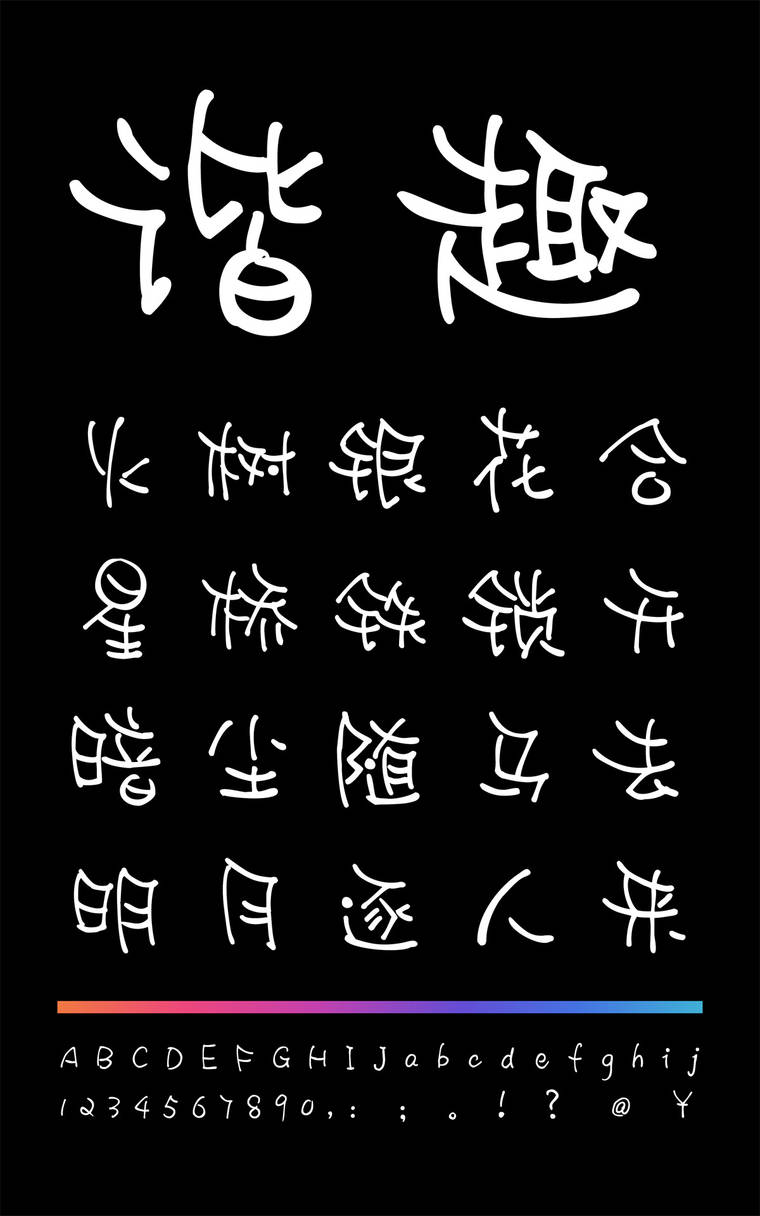
小豆岛惠中谐趣简繁
小豆岛惠中谐趣简繁字体介绍
字体特征:结构整体为倾斜的特点,通过正统书法笔画间架的解构,制造一种重心倾斜的视觉感,笔画活泼,字体笔画简单稚拙,宽细一致,充分体现出活泼谐趣的特点。是一款独特手写字体 字体整体风格统一的特点。应用性强,可以拉伸使用,线条富有节奏与灵气,灰度均匀,点缀生动,具有水墨特点。